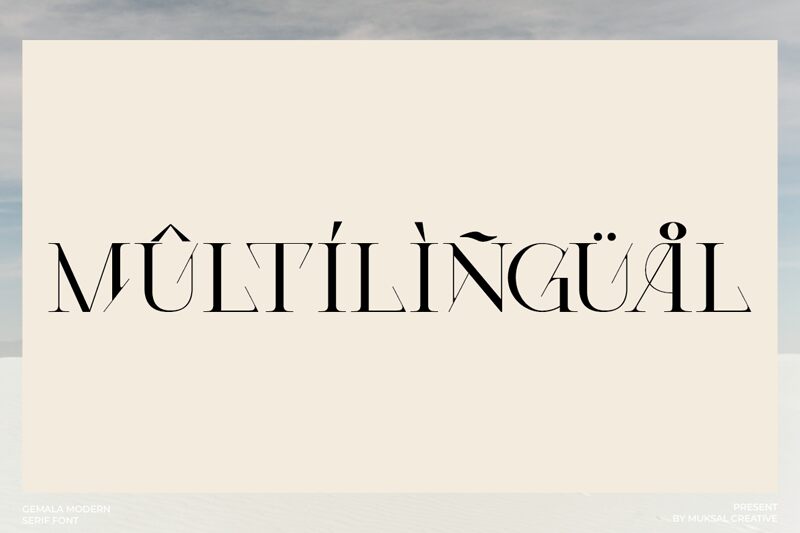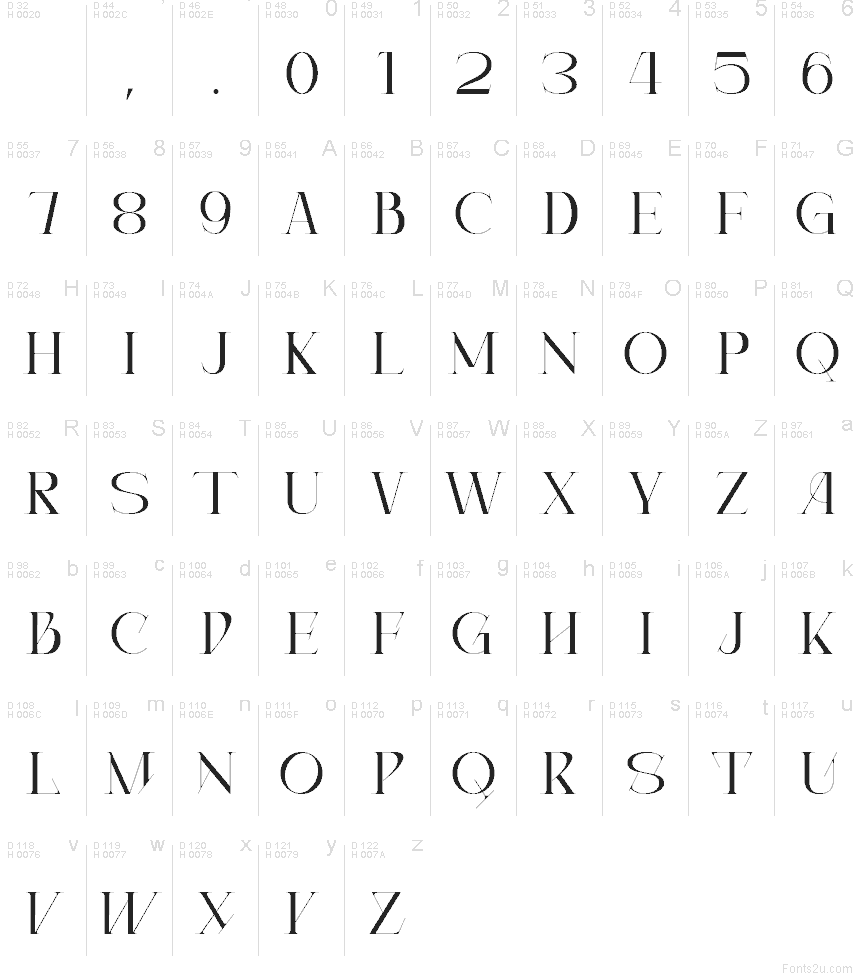
Gemala od Muksal Creative je bezplatné retro písmo typu display, které vyniká vysokými, výraznými tvary, do nichž jsou vloženy velmi jemné diagonální a zaoblené řezy. Tento kontrast mezi pevnou vertikální hmotou a nitkovými vnitřními liniemi dodává písmu elegantní, plakátový rytmus, který připomíná spíše módní titulky než klasický vintage styl.
Hodí se pro titulky časopisů, obaly kosmetiky, plakáty na akce, značení butiků i záhlaví na sociálních sítích. Písmo má dostatečnou výraznost pro krátké nadpisy a loga, kde tyto úzké řezy a křivky fungují jako součást grafického stylu, nikoliv jen jako prostá dekorace na běžných písmenech.
Prezentace a vizuální ukázka písma Gemala Regular
Mapa znaků písma Gemala Regular
Mapa znaků písma Gemala Regular: Základní latinka, strana 1
Glyfy písma Gemala Regular — Základní latinka, strana 1